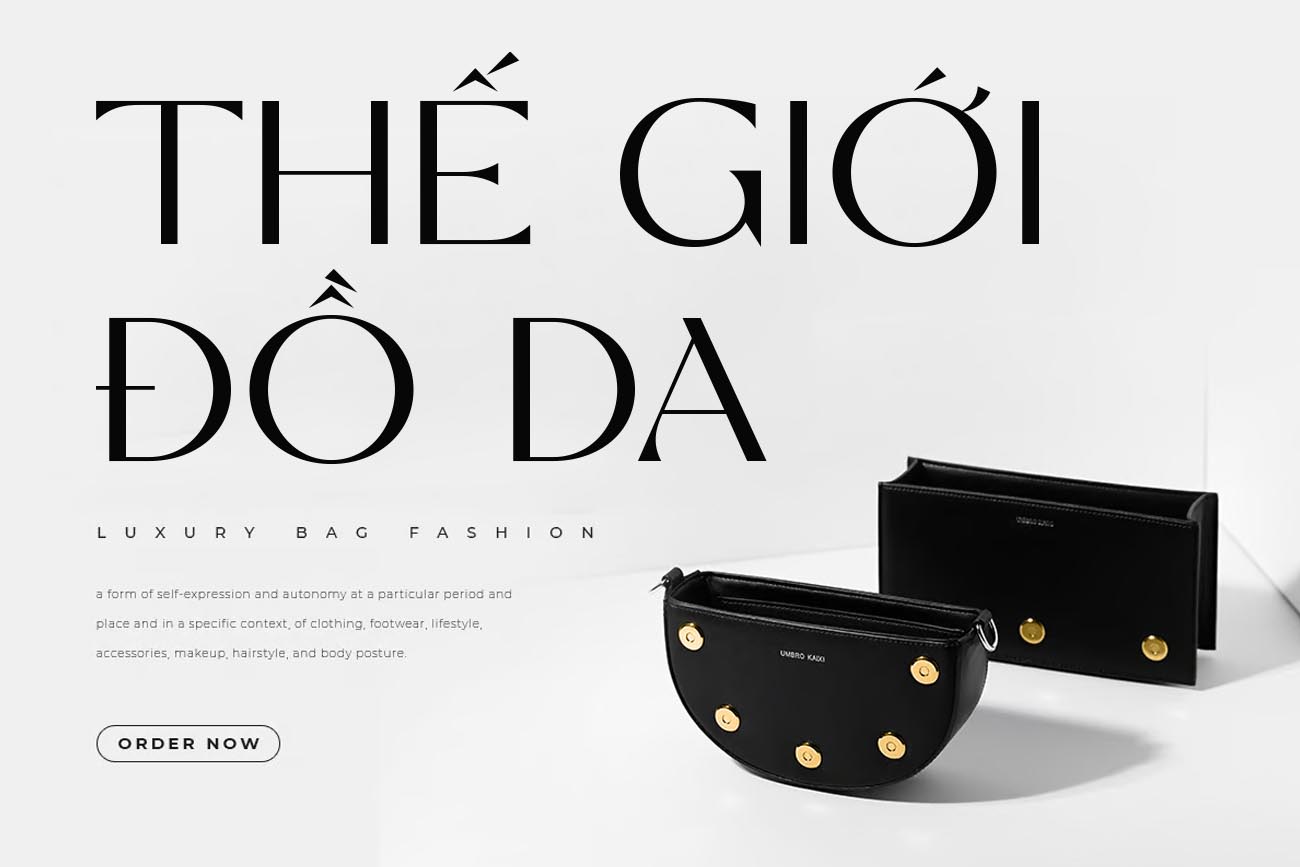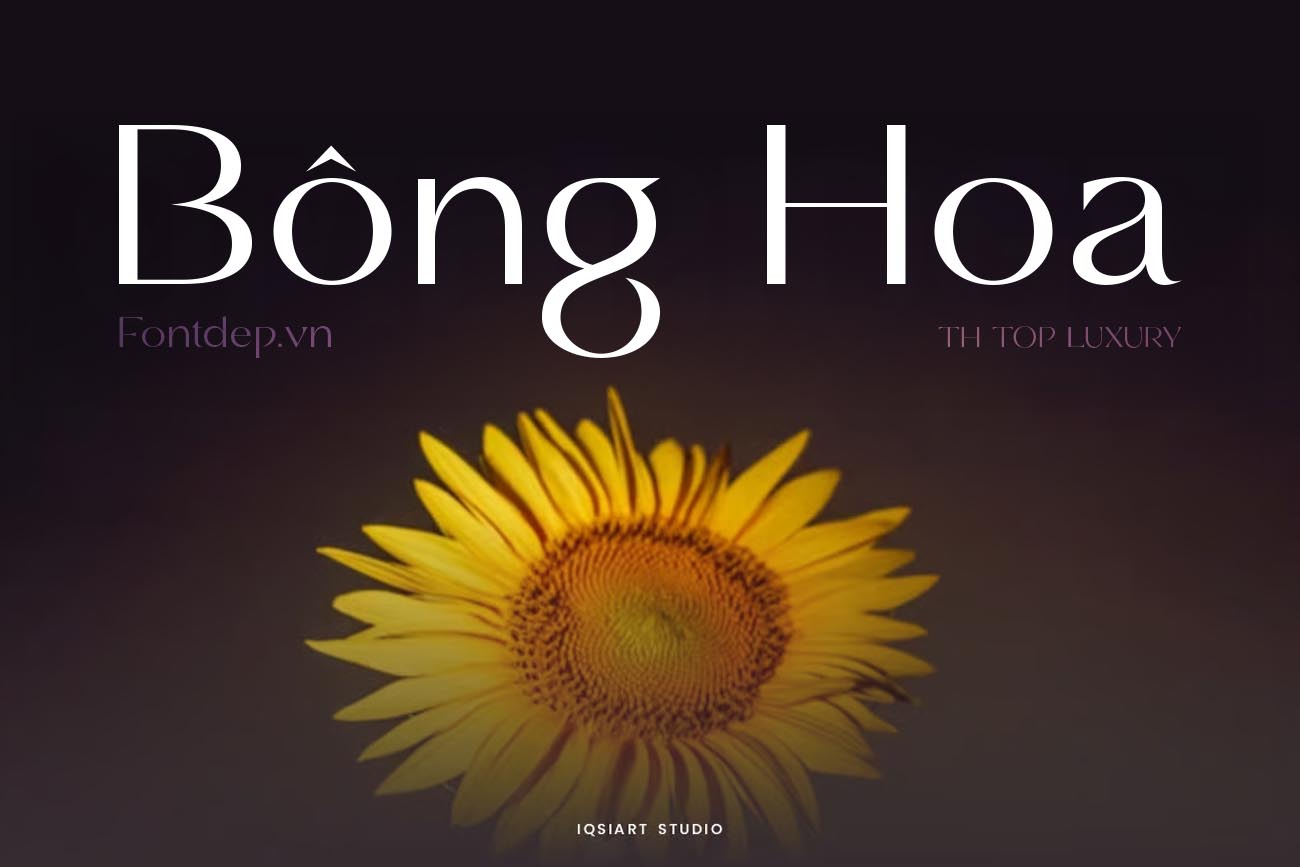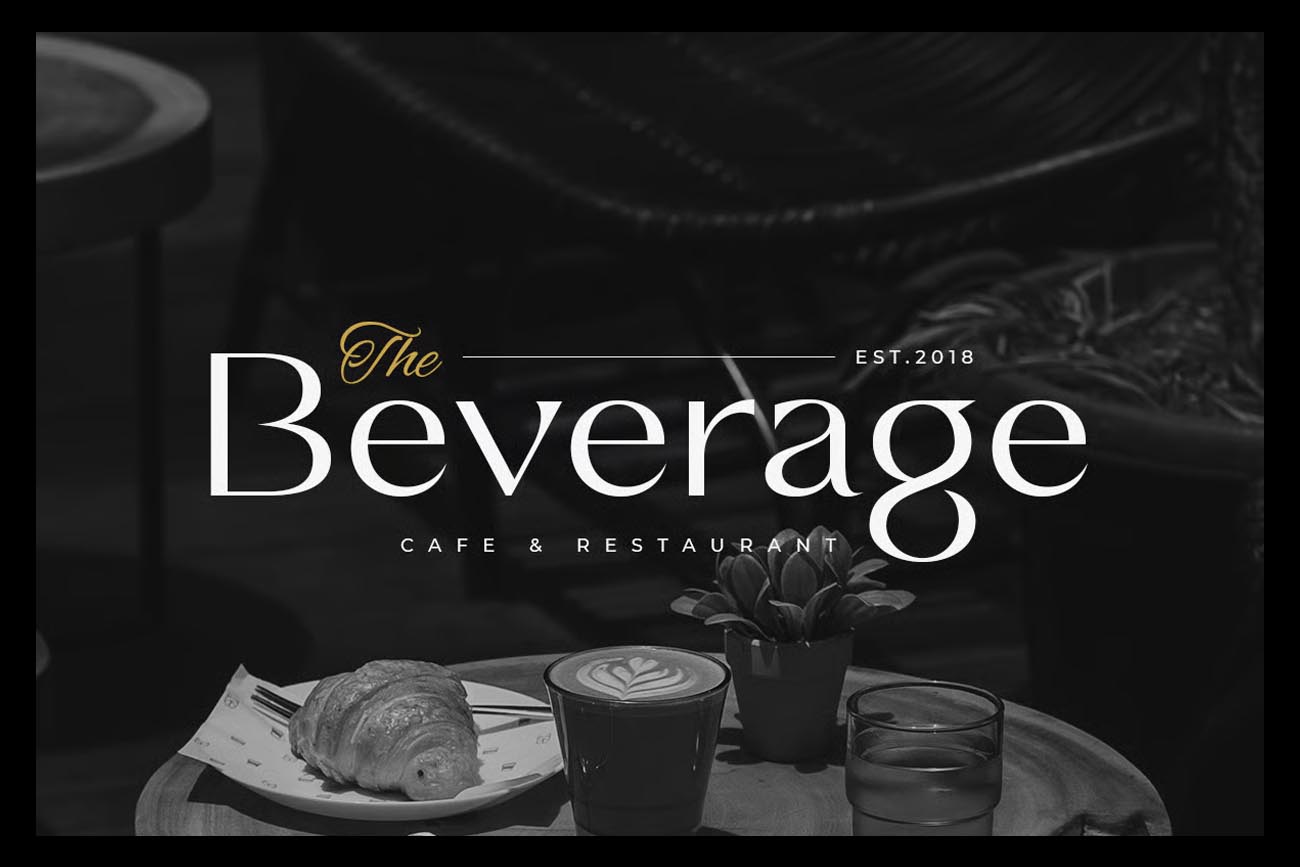
Bạn đang tìm kiếm một font chữ sang trọng với đường nét thanh thoát, có hỗ trợ đầy đủ tiếng Việt? Bộ font TH Top Luxury là lựa chọn lý tưởng cho những ai theo đuổi phong cách thiết kế cao cấp, thanh lịch và chuyên nghiệp.
Giới thiệu font chữ TH Top Luxury
TH Top Luxury là một font chữ serif Việt hóa nổi bật với dáng chữ cao, nét thanh mảnh nhưng dứt khoát. Được phát triển bởi IQSIAART Studio và Việt hóa bởi Fontdep.vn, font mang hơi hướng hiện đại pha chút cổ điển – rất phù hợp cho các thiết kế đòi hỏi sự tinh tế và chuẩn chỉ trong từng chi tiết.
Đặc điểm nổi bật của font TH Top Luxury
• Phong cách: Serif thanh mảnh, cao cấp
• Kiểu dáng chữ: Đường cong mềm mại kết hợp với các nét gãy tinh tế
• Chữ hoa: Thiết kế sang trọng, phù hợp làm tiêu đề, logo
• Việt hóa: Đầy đủ dấu tiếng Việt, cách điệu nhẹ nhàng mà vẫn dễ đọc
Ứng dụng của font chữ sang trọng TH Top Luxury
Font chữ này được ứng dụng rộng rãi trong các thiết kế cao cấp như:
• Thiết kế logo thời trang, mỹ phẩm, nước hoa
• Bao bì sản phẩm sang trọng
• Poster, lookbook, namecard cho thương hiệu cao cấp
• Website, banner giới thiệu sản phẩm nội thất, phong cách sống
• Thiệp cưới hiện đại, elegant
TH Top Luxury là một trong những font chữ serif Việt hóa đẹp nhất năm 2025, lý tưởng cho các thiết kế cần sự đẳng cấp và cuốn hút. Nếu bạn đang làm việc trong lĩnh vực sáng tạo, branding hay thiết kế mỹ thuật, đừng bỏ qua bộ font chữ thanh lịch và chuyên nghiệp này.